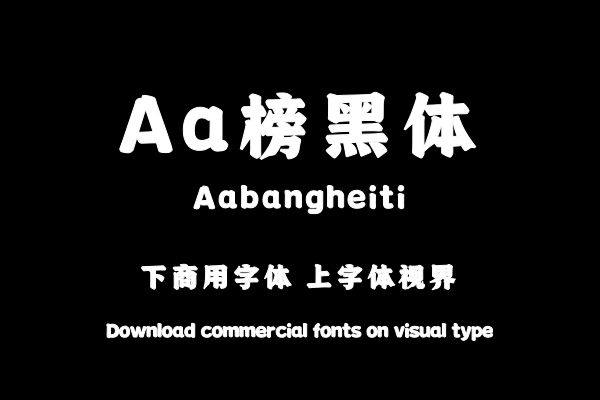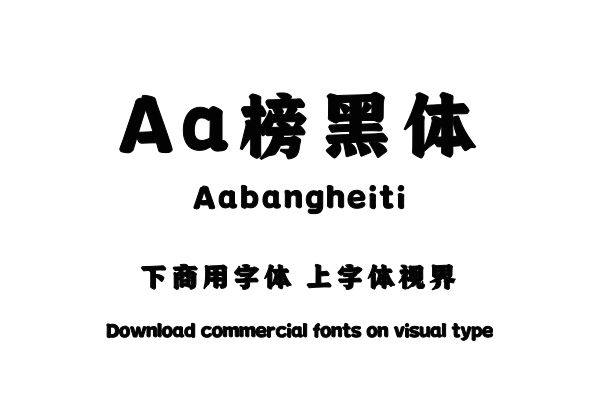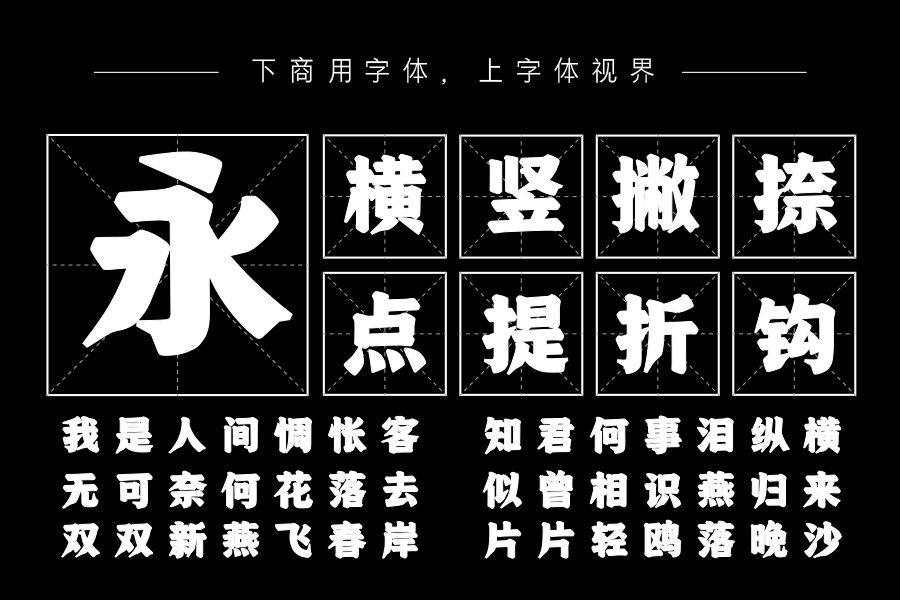
结合榜书写法与雕版韵味重塑一款厚重黑体。将书法中的榜书写法与黑体结合,形成一款稳重厚实的创意标题字体,醒目突出之内饱含书法韵味。购买须知:“下载服务费”与“字体VIP”所获得字体 仅用于个人非商用, 商用请联系付费授权。本字体为电脑用字,手机没有root权限不支持直接手机换字(手机如何root,请自行百度搜索教程)。购买前请先 了解清楚后再付款 ,字体为虚拟产品无法回收 一旦购买不支持退款。